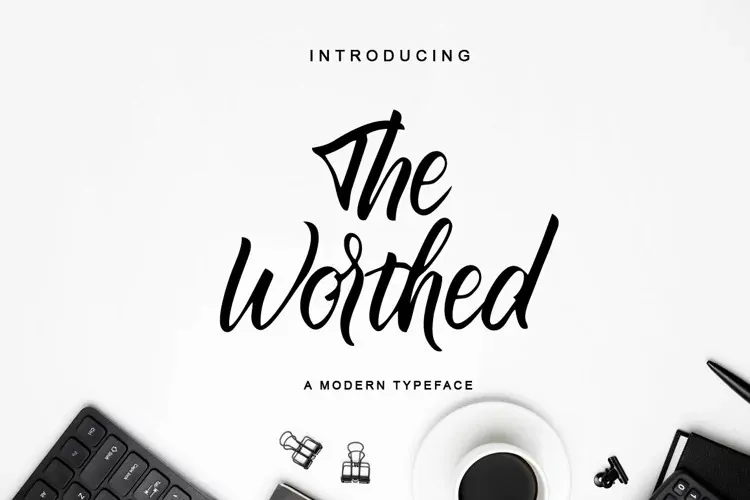
A The Worthed Font é uma tipografia script contemporânea criada pela fanastudio com uma influência natural das mãos humanas. Seu estilo retrata a fluidez e espontaneidade do desenho à mão, sem perder o cuidado em destacar os traços rápidos e detalhes finos que são tão importantes para transmitir um forte e agressivo mensageiro. O resultado é uma fonte ideal para uso nos logotipos, roupas e acessórios personalizados, bem como nas embalagens de produtos e qualquer outro material onde o texto precisa ser expresso com a velocidade e força que os desafiam. A The Worthed Font é perfeita para aqueles que buscam uma fonte agressiva e moderna para seus projetos visuais.